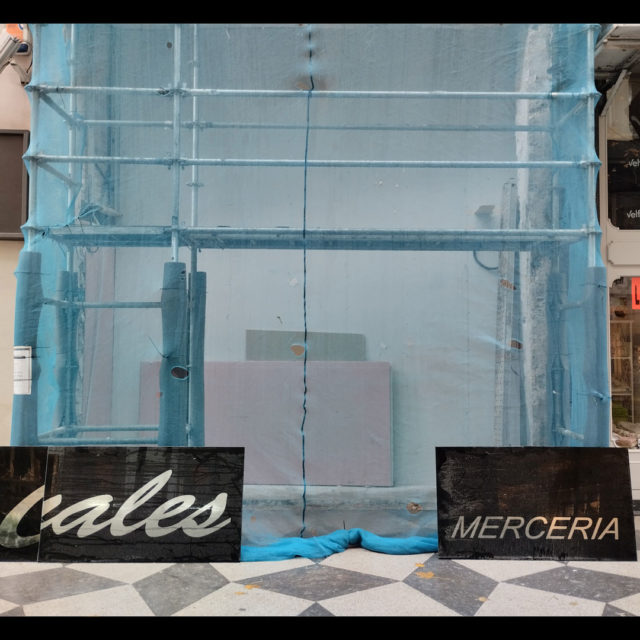
Salvados los cristales de la Mercería Canales
Esta semana hemos recogido los cristales de la vieja “Mercería Canales” en la calle Isabel II.
Fue de los primeros comercios abiertos en la nueva calle creada tras el Incendio de 1941. Cerró sus puertas en 2021. Aunque es un rótulo más moderno y vinilado, sustituyó hace varios años al original que desgraciadamente fue destruido por acabar roto y por el riesgo que suponía para los viandantes. Por fortuna, de ese, tenemos una foto de archivo gracias a la labor documental realizada entre los años 80 y 90 Jose Miguel Rodríguez Castillo, cuya parte del fondo ya tenemos digitalizado. Esta foto también la tenéis en el libro que se publicó en 2020 y que tenéis disponible en libros.com o vuestras librerias de confianza.